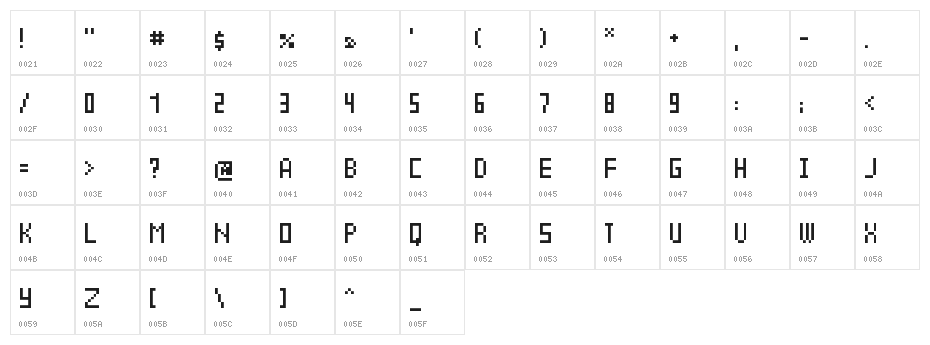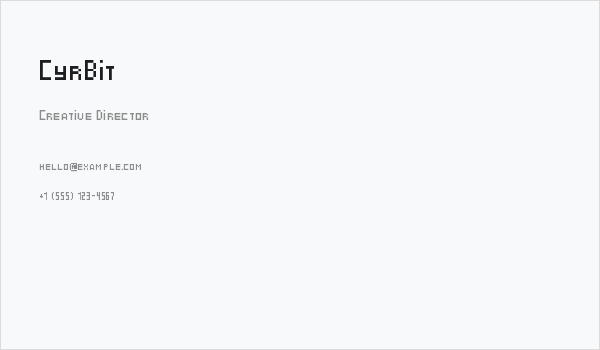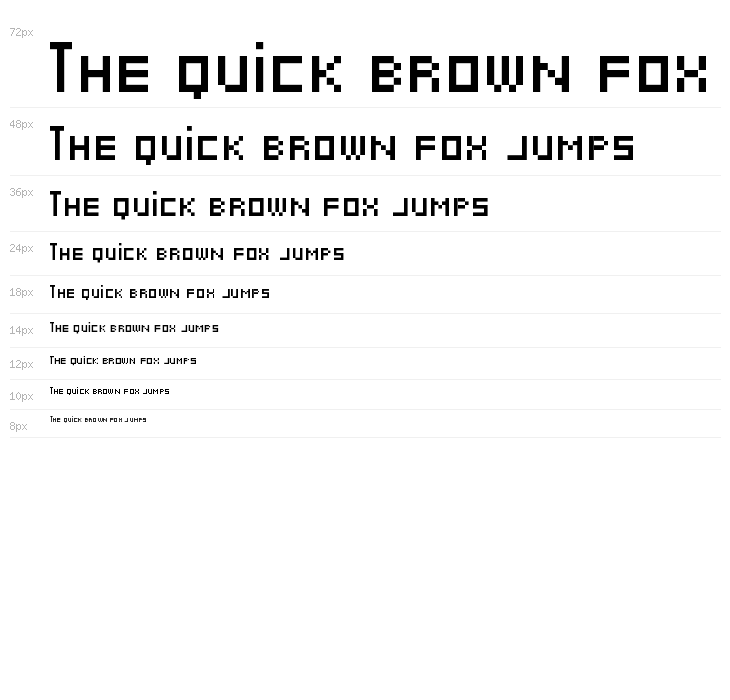
CyrBit Font
✎ Pixel
| Kategorien | Pixel |
| Gesamtstil | Retro, Digital |
| Anwendungsfall | Headlines, Logos, Digital Art |
| Vorgeschlagene Projekte | Ideal for retro-themed designs, video game graphics, digital art projects, and any creative work that requires a nostalgic or tech-inspired aesthetic. |